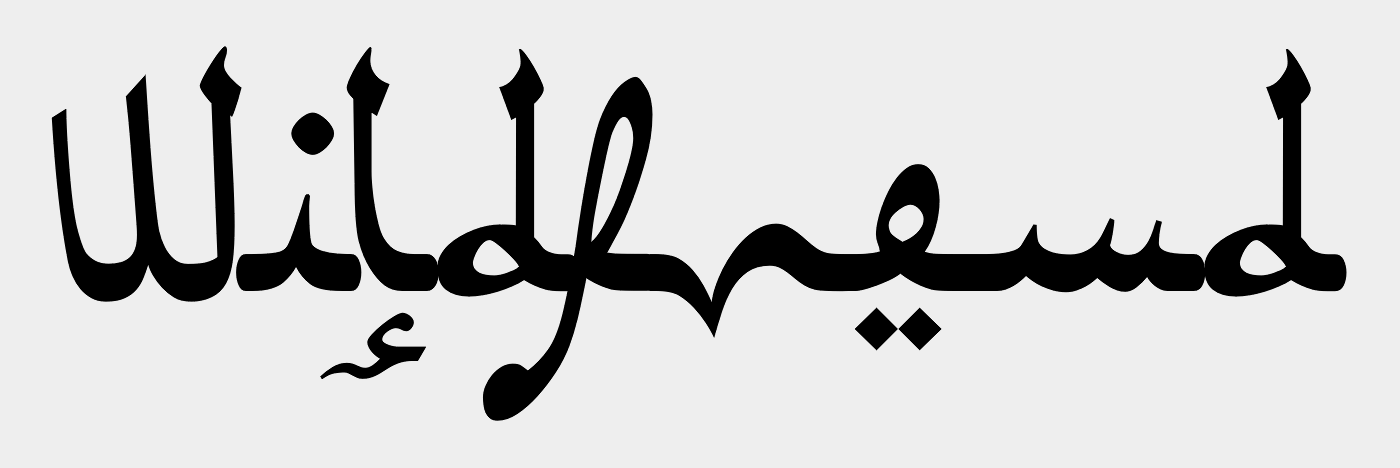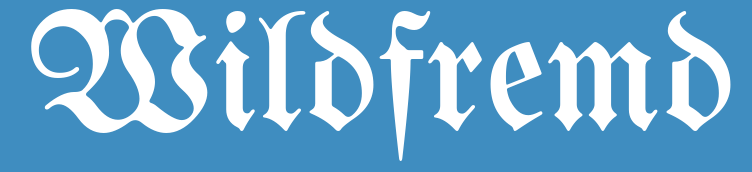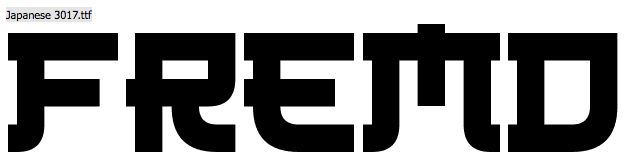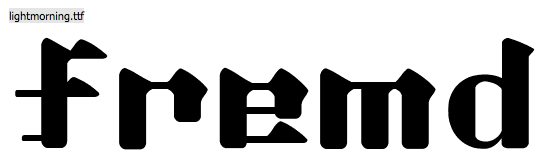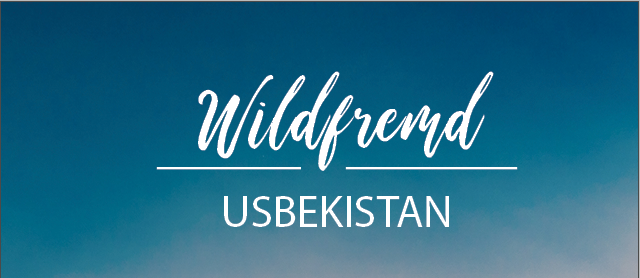
Hilfe zu wildfremd
ich bräuchte mal eure Hilfe. Ich soll in einem Projekt über ein Land ein Magazin erstellen. Der Titel bzw Logo für das Magazin wurde uns vorgegeben "wildfremd" (kann geschrieben werden, wie wir wollen). Ich tue mich total schwer mit der  Schriftartwahl. Ich hatte schon eine Idee mit einer Handschriftlichentypo aber das war zu "lieb". Vielleicht hat jemand von euch eine Idee??
Als alter Freund der Wortspiele kam mir bei Usbekistan gleich "wild" und "fremd" in den Sinn – vielleicht kann der Titel auch so lauten, wo er doch geschrieben kann, wie ihr wollt? Wild und fremd ließe sich dann in zwei unterschiedlichen Stilen umsetzen, eine wilde Handschrift für "wild" und eine auf fernöstlich gemachte Schrift als Hinweis auf chinesische Handelswaren, Seidenstraße, Zentralasien etc. für "fremd". Ist nur ein Gedanke …
Ich hab mir mal auf die Schnelle die Kandidaten für "Faux Chinese/Japanese" auf dafont angesehen – und das meiste finde ich ausgesprochen kitschig. Am ehesten ginge wohl noch sowas:
das Land hat nicht wirklich was mit dem Logo zu tun, von daher muss es nichts aus dem asiatischen Raum sein
ich würde – bezugnehmend auf die frühere sowjetische teilrepublik – mit kyrillischen formen spielen. gib t dort eh auch eine abteilung »russisch«
das Land hat nicht wirklich was mit dem Logo zu tun, von daher muss es nichts aus dem asiatischen Raum sein
Verstehe ich richtig, dass Du Dir das Land aussuchen kannst? Welches möchtest Du denn wählen? Oder ist es Lummerland oder Fantasia?
Erst wenn das Land klar ist, würde ich den Ausspruch gestalten. Andersherum geht vielleicht auch, scheint mir aber schwierig zu sein.
Außerdem scheint mir interessant zu sein, wer von dem wildfremden Design des Logos angesprochen werden soll. Es könnte ein Tuareg sein, der eine Reise zum Nordpol machen möchte.
Vielleicht erarbeitest Du Dir mit diesem Ansatz einen Sonderpunkt. Und lass Dir nicht erzählen, Tuaregs könnten keine Magazine lesen.
Ich will damit auch sagen, dass man mehr Ideen von Dir braucht, um helfen zu können.
Na ja, also ich würde den (ja anscheinend nicht zu ändernden) Titel versuchen, zu hinterfragen, zu konterkarieren. Mir gefällt er nämlich gar nicht. Denn was uns wild(und)fremd erscheint, ist den Menschen, die da leben, normal und heimelig. Da symbolisiert der Titel also, dass da gar nicht so das Land beschrieben werden soll, sondern die Perspektive des naiven (und wohl weißen, wahrscheinlich vergleichsweise prililegierten) Betrachters, dessen Vorfahren solche Beobachtungen oft aus der Perspektive des Kolonialherren gemacht hat, der die lokalen »Wilden« !!!! zivilisieren wollte.
Bliebe (für mich) also die Frage, wie ich das anstellen würde. Vielleicht mit einer gebrochenen Schrift? Die symbolisierte, dass der wildfremde Eindruck eben bestenfalls für Menschen aus dem Frakturkreis gelten könne.
Oder, wenn es weniger typogeekig sein soll, vielleicht als wild?fremd? – oder wildfremd auf einer Wolke aus Fragezeichen – oder der Begriff eben sonstwie »dekonstruiert«. (Mir fällt im Moment da nur das englische deconstructed in seiner Doppeldeutigkeit ein.)
Wild hat für mich auch eine sehr positive Bedeutung. Ich denke dabei an Astrid Lindgren: »Laß dich nicht unterkriegen, sei frech und wild und wunderbar!«
Und bei fremd denke ich zuerst an Karl Valentin, der das Thema Fremde so schön von allen Seiten betrachtet, und das im Jahr 1940.
»wildfremd« kann also auch bedeuten, daß uns etwas Fremdes noch wunderbar spannend vorkommt; wir fahren genau deshalb dorthin, damit uns das Fremde danach nicht mehr fremd ist.
Mir fehlen dazu ja noch ein paar Infos: Wer ist die Zielgruppe, was genau ist das Thema – soll das Land im Allgeminen dargestellt werden unter dem Gesichtspunkt der Andersartigkeit zu unserer Gesellschaft*, oder geht es wirklich um Wildniss und Abenteuer in der usbekischen Steppe? Das müsste man erst klären oder im Falle einer freien Arbeit im Studium selber festlegen. Dann kann man auch gezielter arbeiten.
das war zu "lieb".
Warum? Muss Fremdartigkeit mit Gefahr einhergehen? Das Klischee der wilden Kannibalen kann man auch mal ad Acta legen und den Schwerpunkt auf interessante Andersartigkeit und Entdeckerlust richten. Hier kann so eine Schrift gut passen. Vielleicht könnte sie in der Tat extremer, verspielter und weniger einfach zu entschlüsseln sein, so dass sie erst als Bild wirkt und beim zweiten Blick die Aussage erkennbar ist. Vielleicht könnte man das schon aus der Vorlage oben erstellen.
Wie fändest du ein Magazin über Schwule mit einem unironischen Titel Wildfremd? Über Frauen? Juden? Ossis?